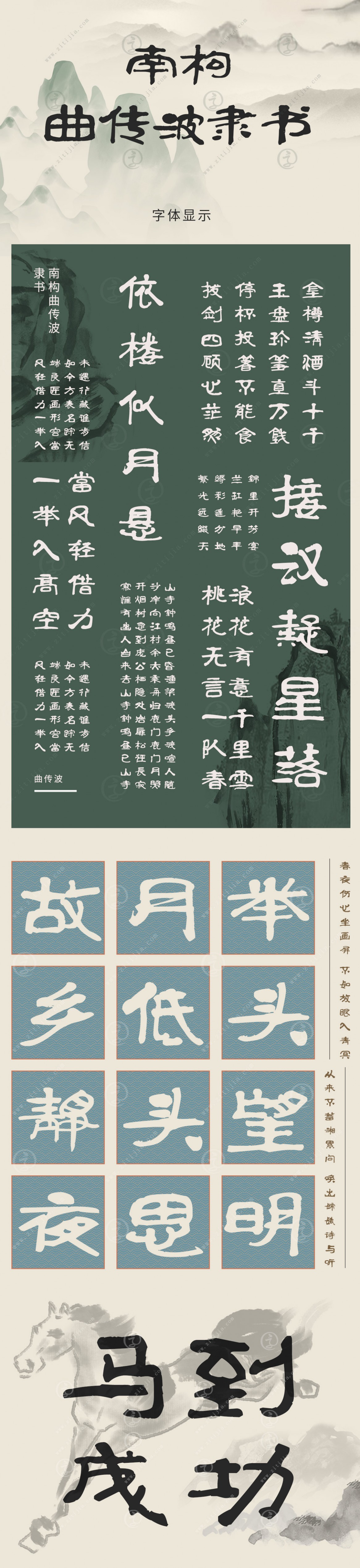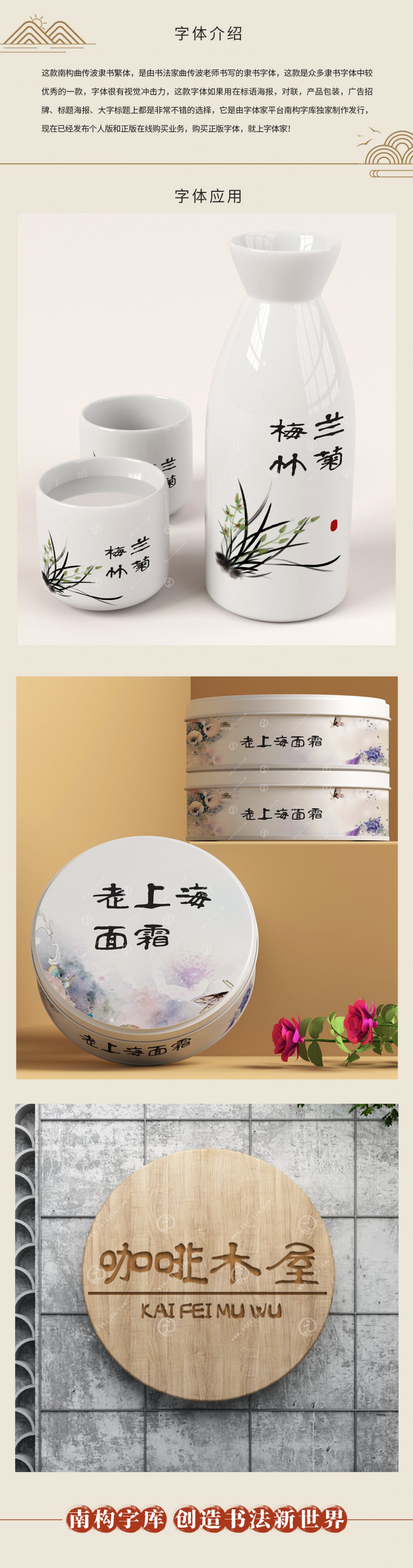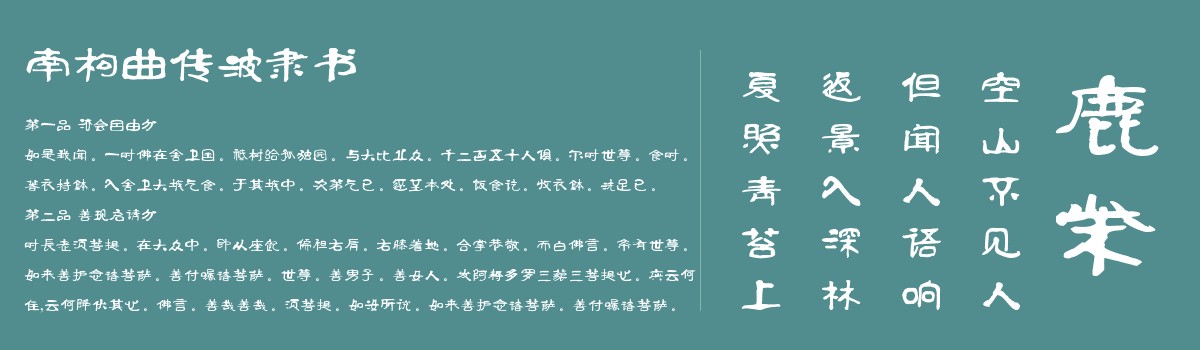
南构曲传波隶书
是由书法家曲传波老师书写的隶书字体,曲传波老师不仅发布了隶书字体,还发布了草书和隶书繁体,这款隶书还有一款同样风格的繁体隶书,隶书字体相对于其他字体来说,适用范围会更广,这款是众多隶书字体中较优秀的一款,特别推荐给朋友们,这款字体如果用在标语海报,产品包装,广告招牌上都是非常不错的选择,由字体家平台南构字库独家制作发行,现在已经发布个人版和正版在线购买业务,购买正版字体,就上字体家!